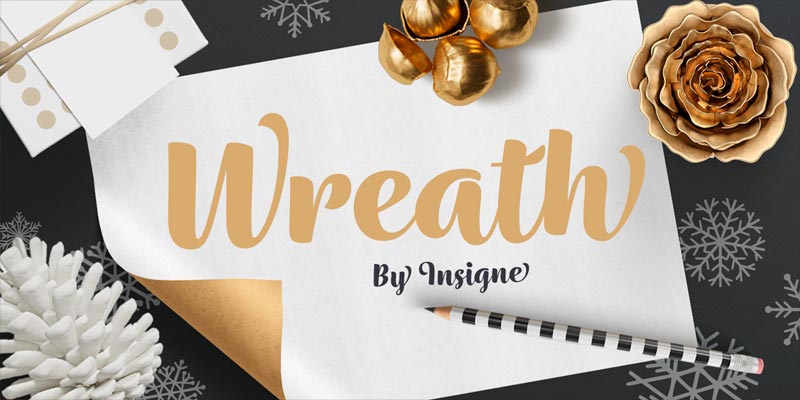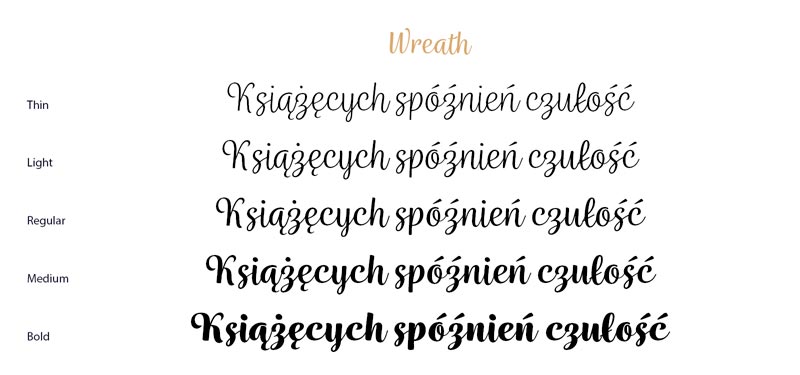
Font Wreath
Nabyliśmy nowy ozdobny font Wreath, który znajdzie zastosowanie przy składzie czasopism “beauty” i “hand made”.
Cała rodzina składa się z pięciu odmian wagowych i kilkunastu wariantów o różnym teksturowaniu.